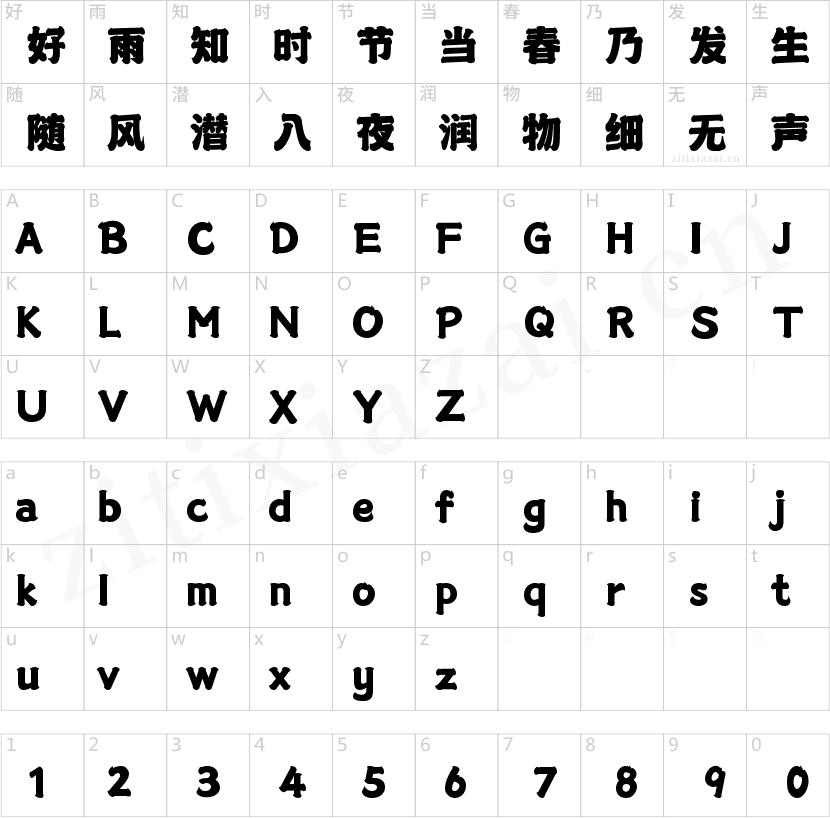
字魂状元榜书
字魂状元榜书,这款字体结构工整、笔画清晰,兼顾美观与易读性,适用于标题、正文、海报、包装、LOGO 等多种场景。字形优雅稳定,风格百搭耐看,适配日常排版与创意设计,让文字呈现更舒适、更具质感。字魂状元榜书一笔一画,皆是细节,以均衡的比例、流畅的线条打造舒适视觉体验,字形端正大气,风格简约现代。无论是商业设计、品牌宣传还是日常排版,都能轻松驾驭,让文字更有格调与力量。字魂状元榜书字体下载。